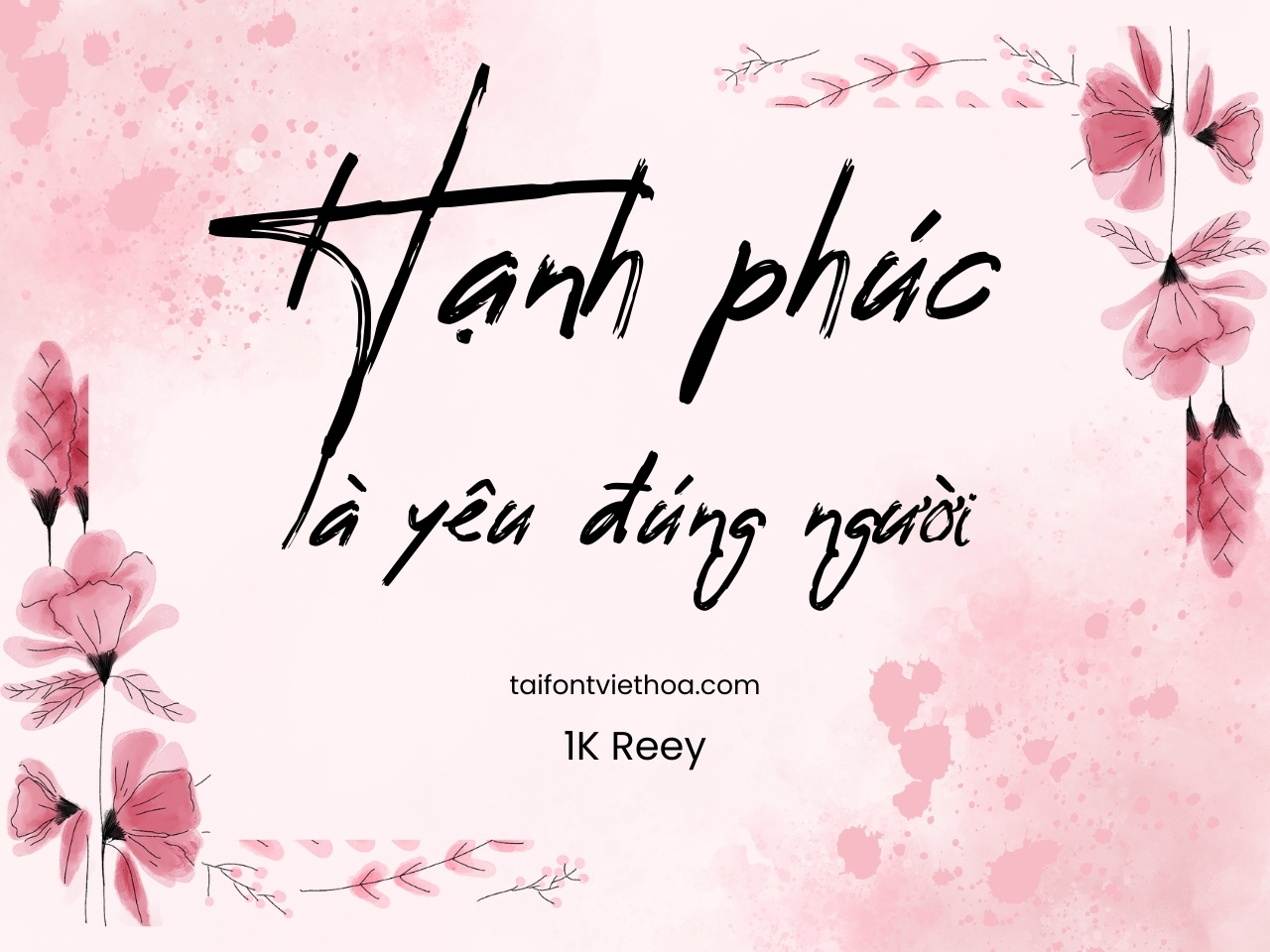
Giới thiệu về font 1K Reey – Nét viết tay hiện đại của Koen Van Der Bliek
1K Reey là một kiểu chữ viết tay mang phong cách hiện đại và tự nhiên, được thiết kế bởi Koen Van Der Bliek – một nhà thiết kế người Hà Lan chuyên về các font script và handwritten. Font mang đến cảm giác gần gũi, chân thực như được viết bằng bút lông mềm mại, phù hợp với các thiết kế mang tính cá nhân hóa hoặc cảm xúc. Phiên bản Việt hóa của 1K Reey do Fonttiengviet thực hiện, hỗ trợ đầy đủ tiếng Việt cùng hơn 100 ngôn ngữ khác trên thế giới. Font này đã được taifontviethoa.com chọn lọc, đánh giá kỹ lưỡng và chia sẻ đến cộng đồng thiết kế Việt nhằm phục vụ các ứng dụng thực tế như typography sáng tạo, thiết kế thiệp mời, bìa sách, hay truyền thông thương hiệu mang dấu ấn cá nhân.
Đặc điểm thiết kế của 1K Reey và các ứng dụng trong sáng tạo
Font 1K Reey có đường nét uyển chuyển, bay bổng với những đường cong mềm mại, thể hiện rõ sự linh hoạt trong từng ký tự. Kiểu dáng chữ thiên về cảm xúc tự nhiên, với các nét nối liền mạch giúp bố cục tổng thể trở nên liền lạc và cuốn hút. Font còn đi kèm một số ký tự thay thế (alternates) nhằm gia tăng tính cá nhân hóa trong từng thiết kế. Nhờ những ưu điểm nổi bật đó, 1K Reey rất thích hợp cho các thiết kế trong ngành quảng cáo, thiệp mời, sản phẩm trang trí, blog cá nhân, hoặc các chiến dịch truyền thông mang hơi hướng lễ hội, sinh nhật, Valentine và các dịp đặc biệt khác. Đặc biệt phù hợp với ngành thời trang, ẩm thực, mỹ phẩm và nội dung sáng tạo cảm xúc.